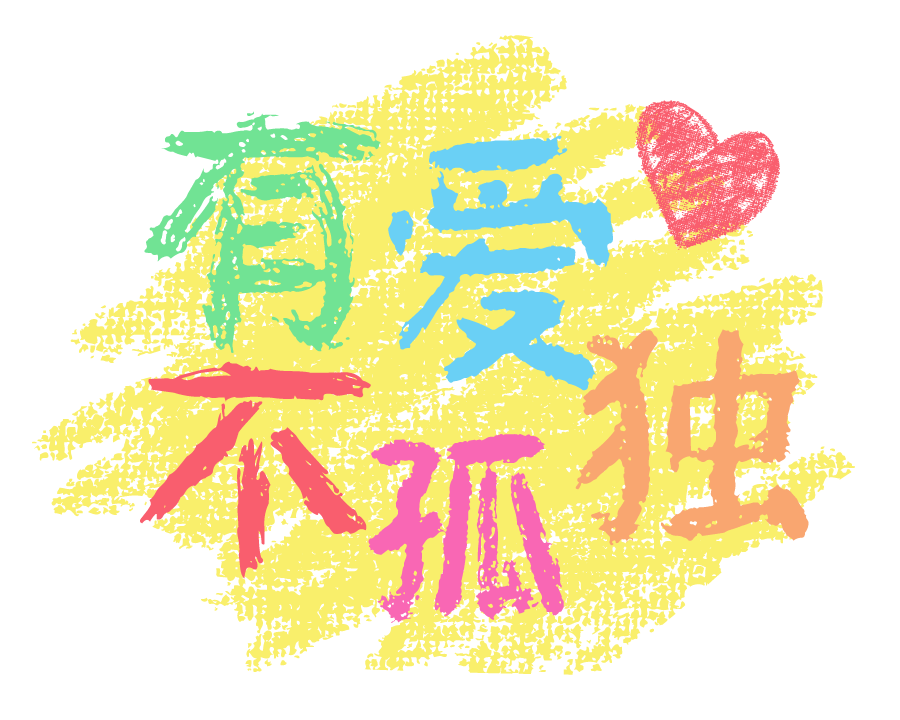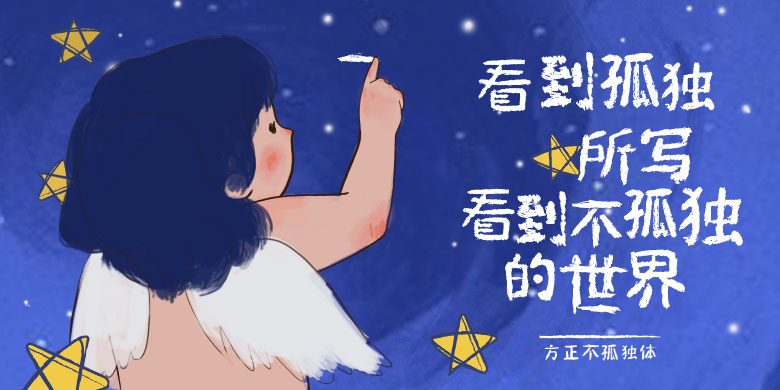
方正不孤独体温暖上线 助力“星宝蓝书包”公益项目
自闭症,也称孤独症。在我国,孤独症及其谱系障碍儿童人数达300万,且孤独症的发病率已居我国各类精神病症之首。第十二个世界孤独症关注日期间,方正IT旗下方正电子、方正手迹以北大医疗脑健康儿童发展中心孤独症小朋友的字体为灵感,结合人工智能造字技术,开发出第一款孤独症儿童参与创作的字体——“方正不孤独体”。该字体于4月3日正式上线,引起了社会对孤独症这一特殊病症和群体的关注与爱护。
“方正不孤独体”个性纯真稚气,笔画圆润稚拙;由于纯手写原因,笔触具有偶然性,单个汉字之间具有不同的特质,每个字都可以独具风情。该款字体可适用于孤独症公益事业宣传活动,在儿童类书籍、产品包装以及趣味性的广告、海报等方面也同样适用。“方正不孤独体”的字体收益将全部捐给中国宋庆龄基金会星宝蓝书包孤独症公益项目,以唤起社会对孤独症的关注。